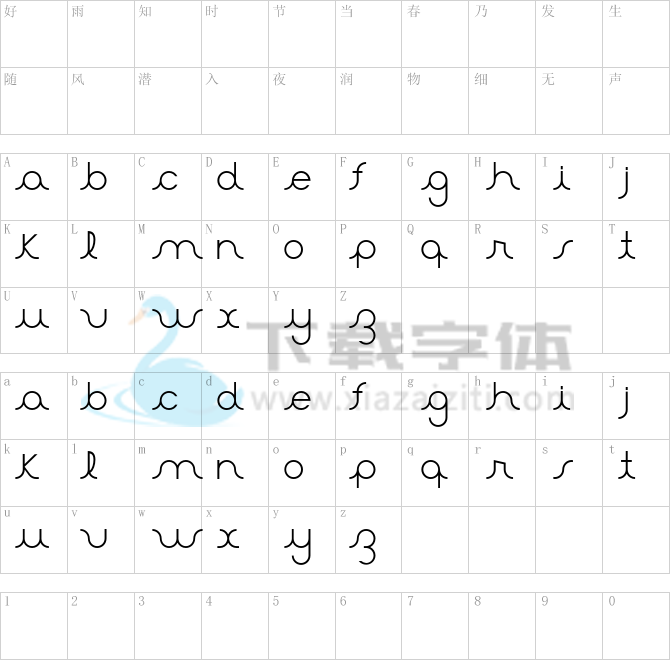
Aster 2.otf字体下载,这款字体结构工整、笔画清晰,兼顾美观与易读性,适用于标题、正文、海报、包装、LOGO 等多种场景。字形优雅稳定,风格百搭耐看,适配日常排版与创意设计,让文字呈现更舒适、更具质感。Aster 2.otf字体下载一笔一画,皆是细节,以均衡的比例、流畅的线条打造舒适视觉体验,字形端正大气,风格简约现代。无论是商业设计、品牌宣传还是日常排版,都能轻松驾驭,让文字更有格调与力量。Aster 2.otf字体下载字体下载。